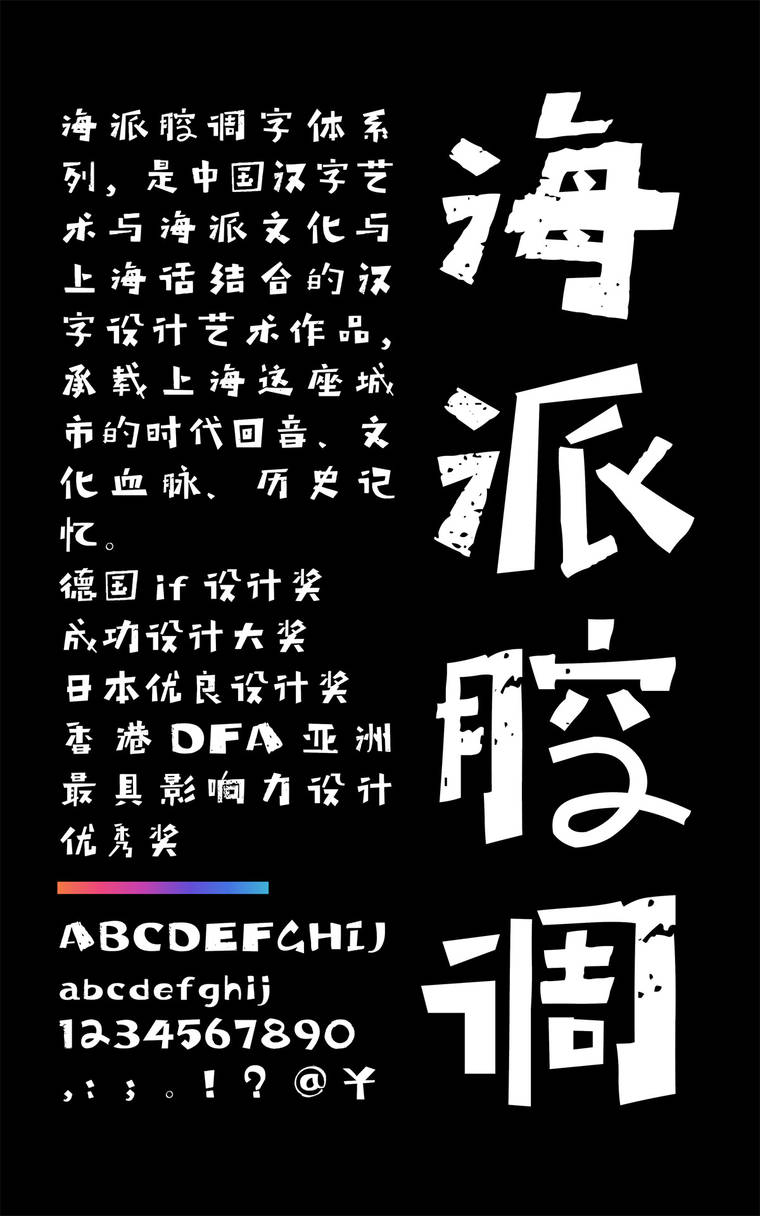
海派腔调禅粗黑简1.0
海派腔调禅粗黑简1.0,这款字体结构工整、笔画清晰,兼顾美观与易读性,适用于标题、正文、海报、包装、LOGO 等多种场景。字形优雅稳定,风格百搭耐看,适配日常排版与创意设计,让文字呈现更舒适、更具质感。海派腔调禅粗黑简1.0一笔一画,皆是细节,以均衡的比例、流畅的线条打造舒适视觉体验,字形端正大气,风格简约现代。无论是商业设计、品牌宣传还是日常排版,都能轻松驾驭,让文字更有格调与力量。海派腔调禅粗黑简1.0字体下载。
字体特征:海派腔调禅粗黑是海派腔调系列里的禅意标题字,错落有致,富于变化,禅味十足。是以汉字艺术与上海海派文化结合的艺术作品。可应用于海报、包装等。